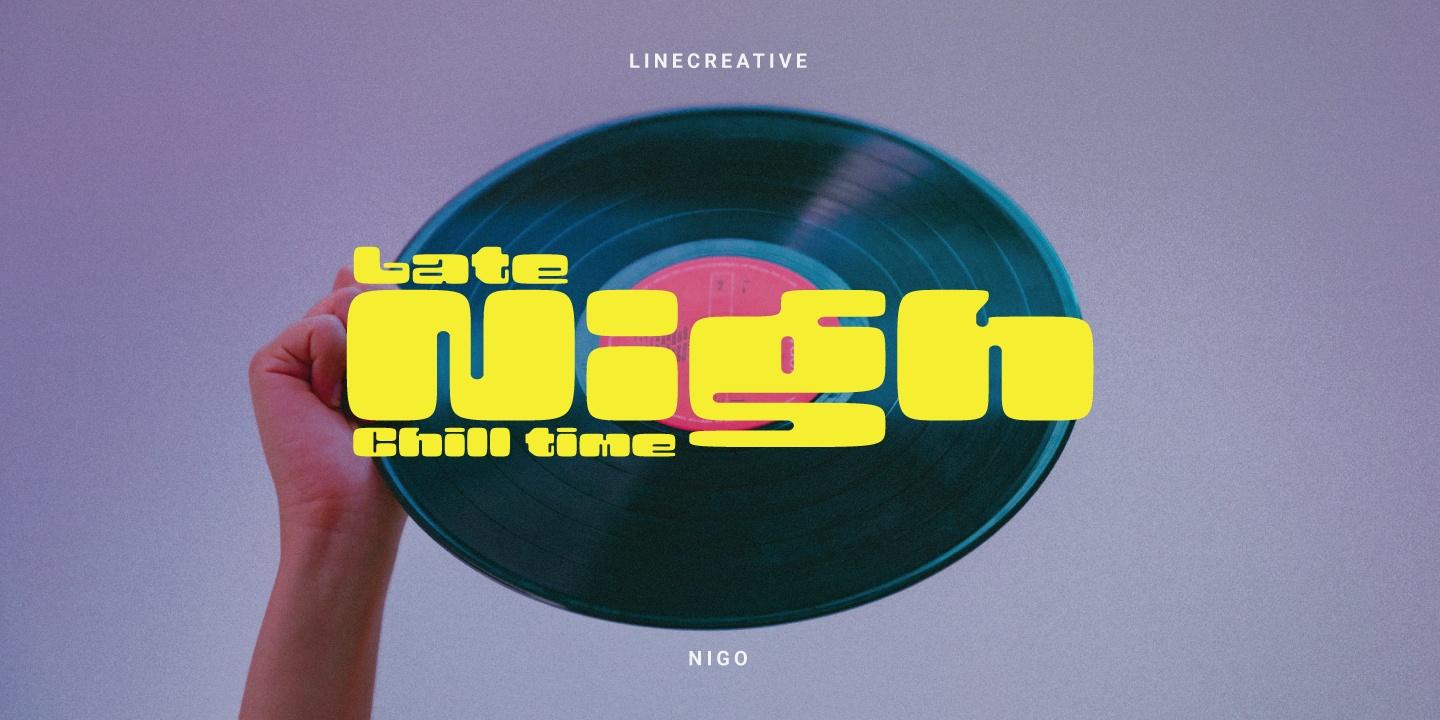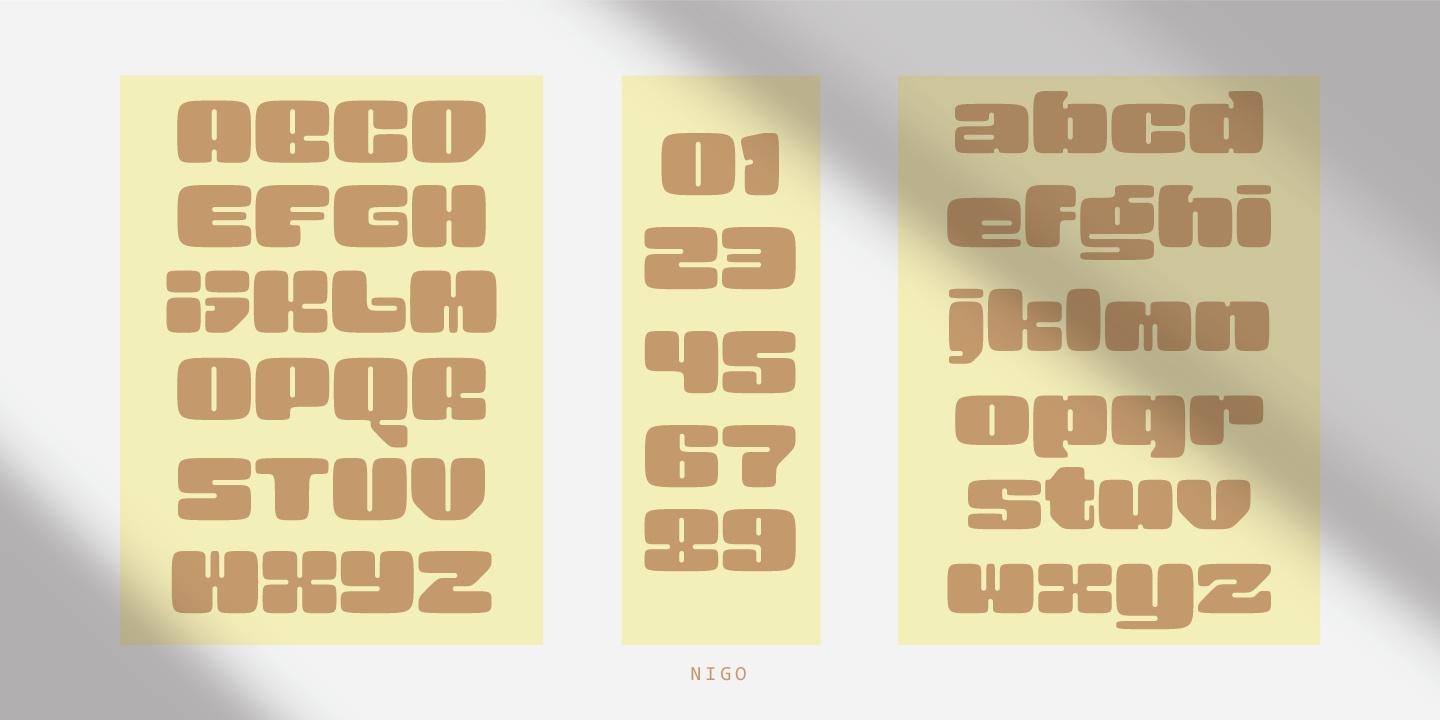
Nigo Font
Description de Nigo Font
Nigo est une police élégante. Elle a un look à la fois moderne et rétro – claire, moderne et amusante, parfaite pour réaliser n’importe quel projet comme un en-tête, une citation, une mise en page de magazine et autres. C’est encore mieux si vous l’utilisez sur un projet de design des années 60 et 70.